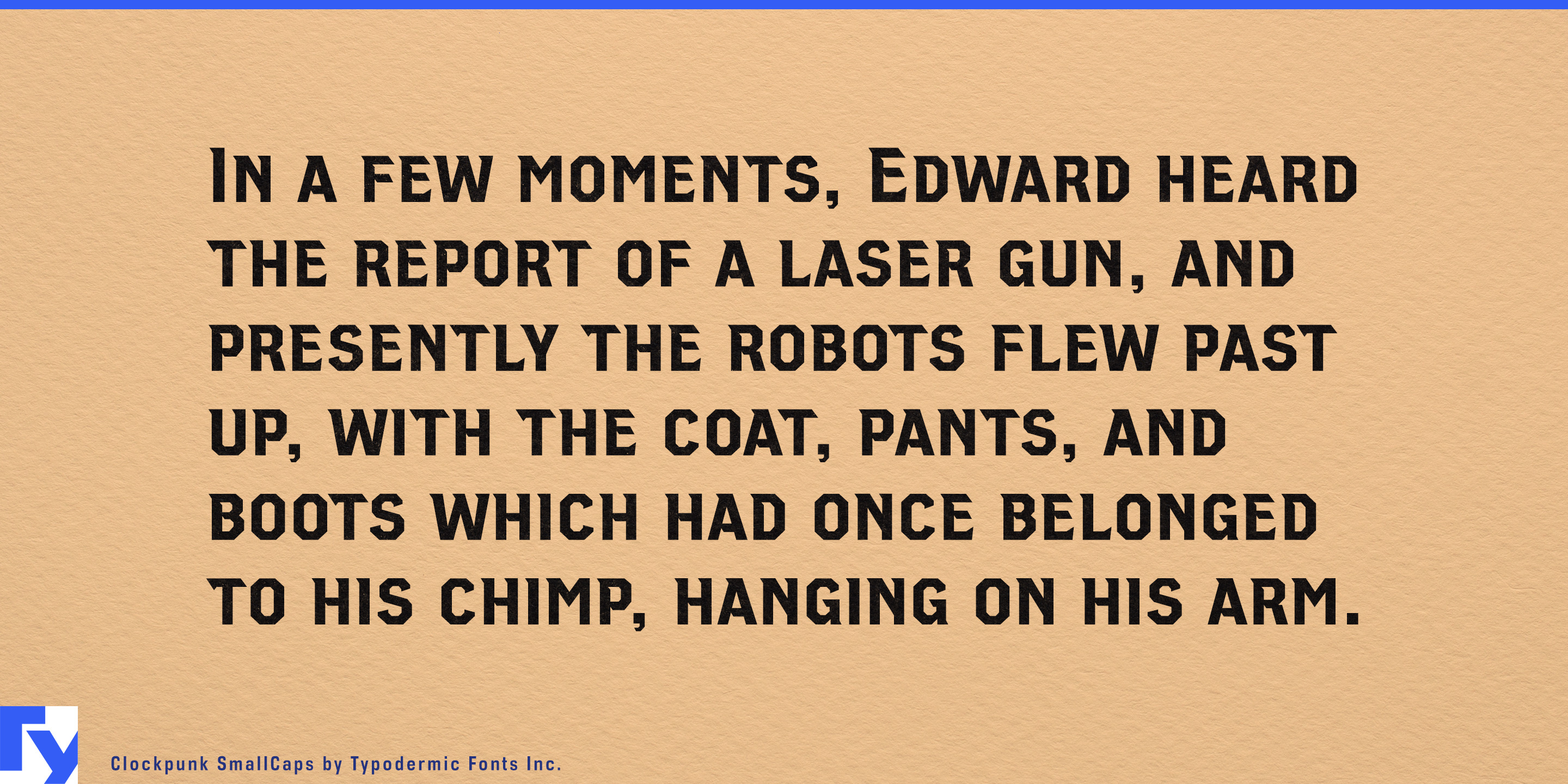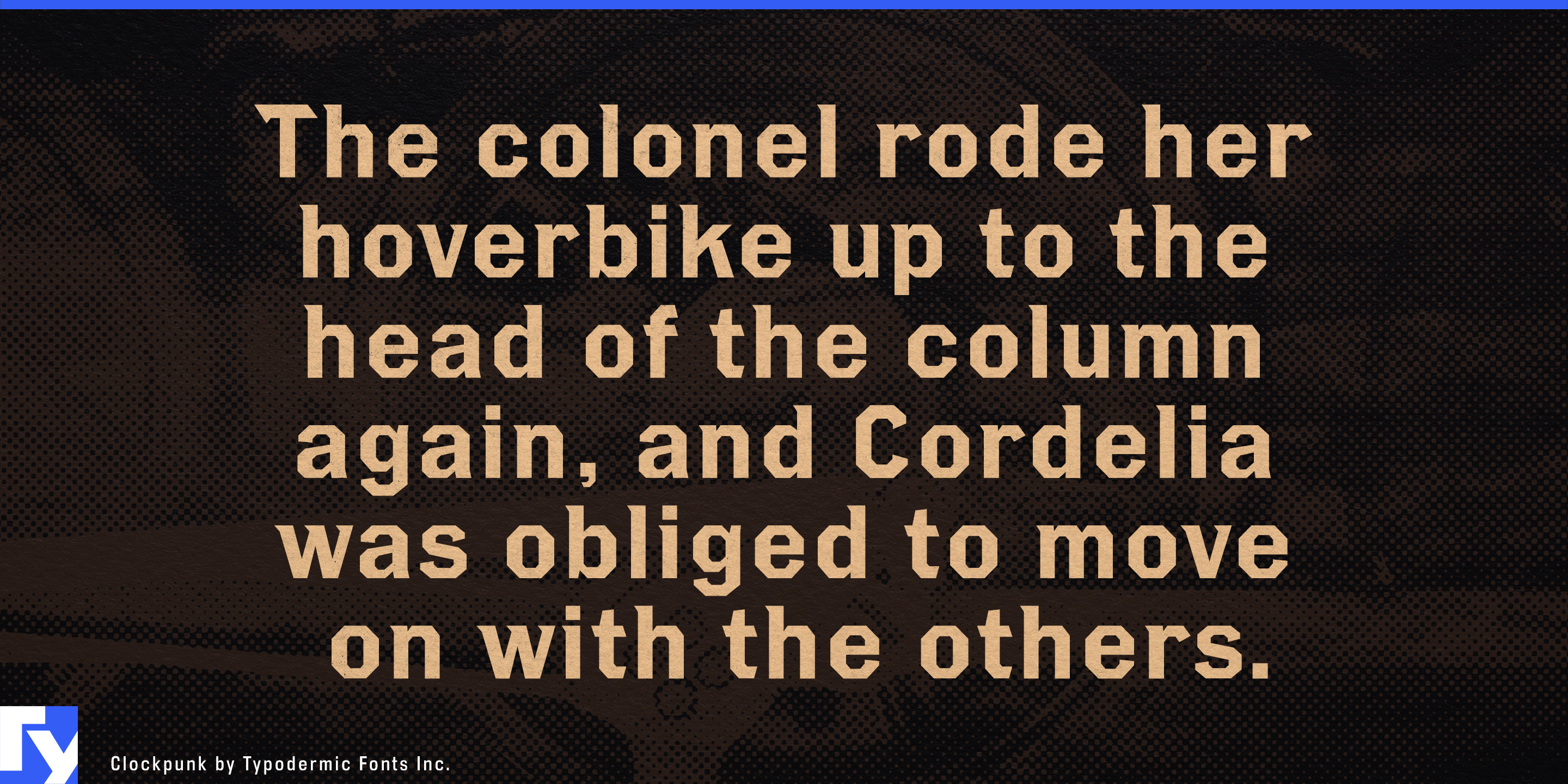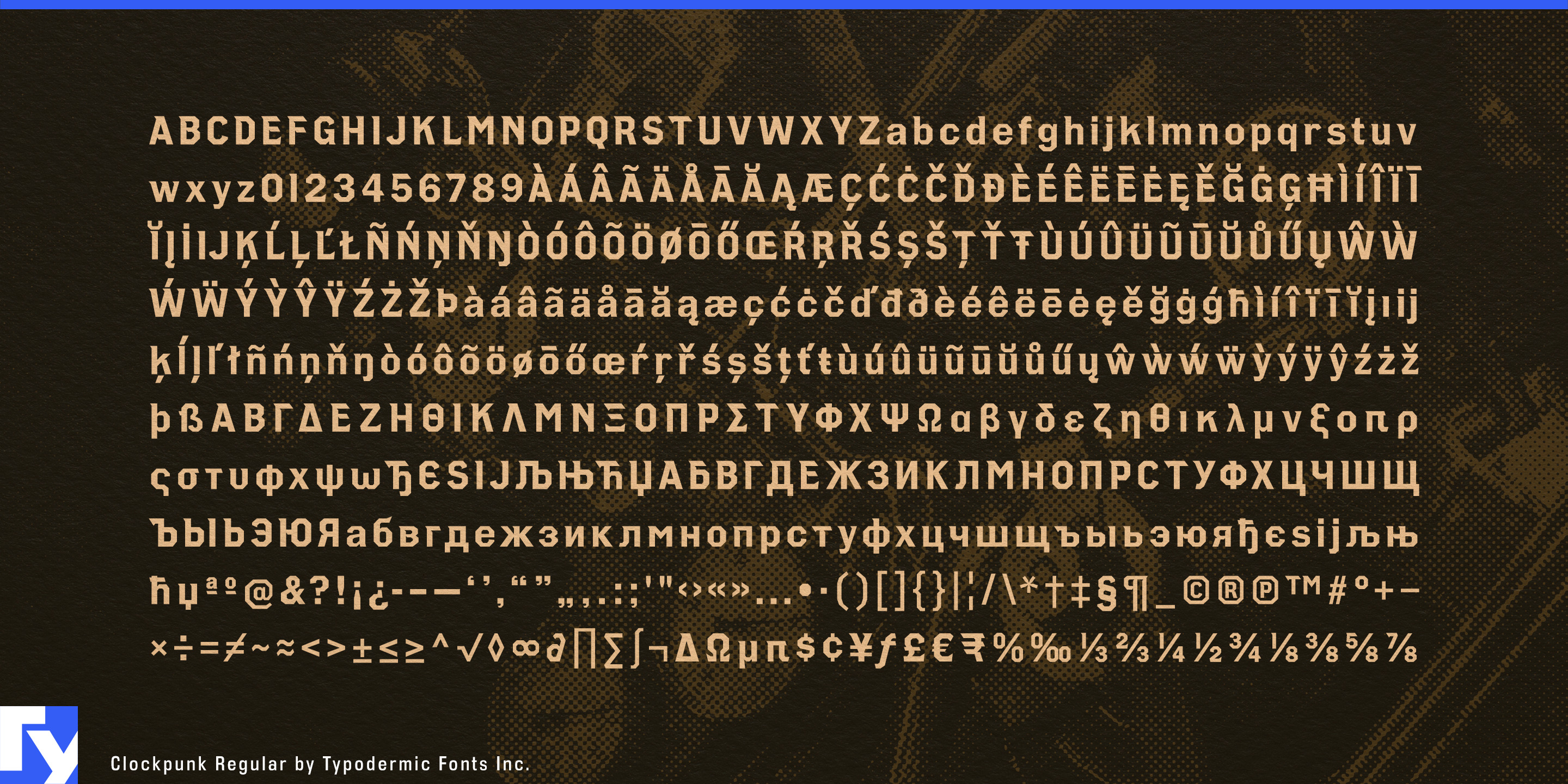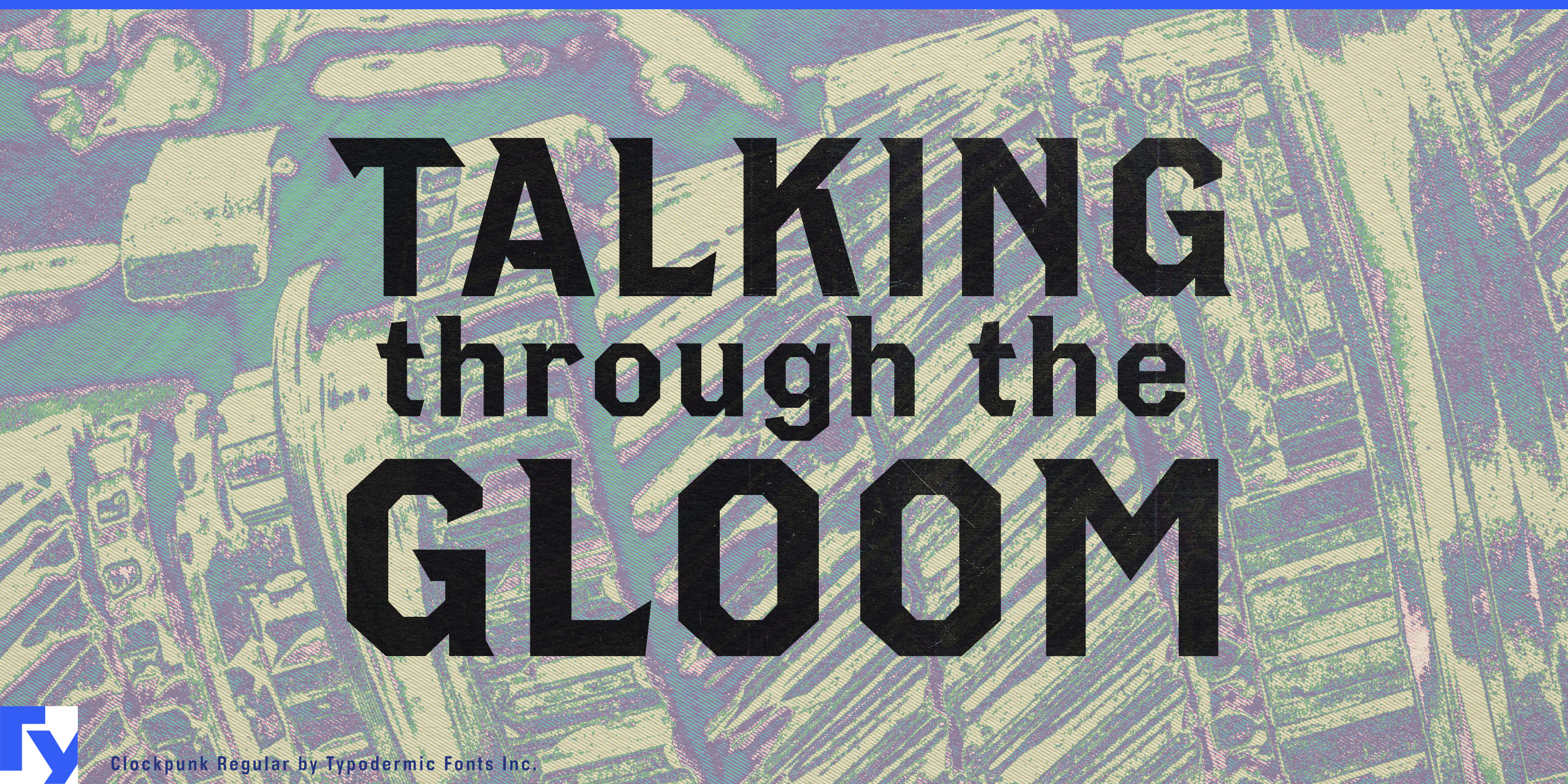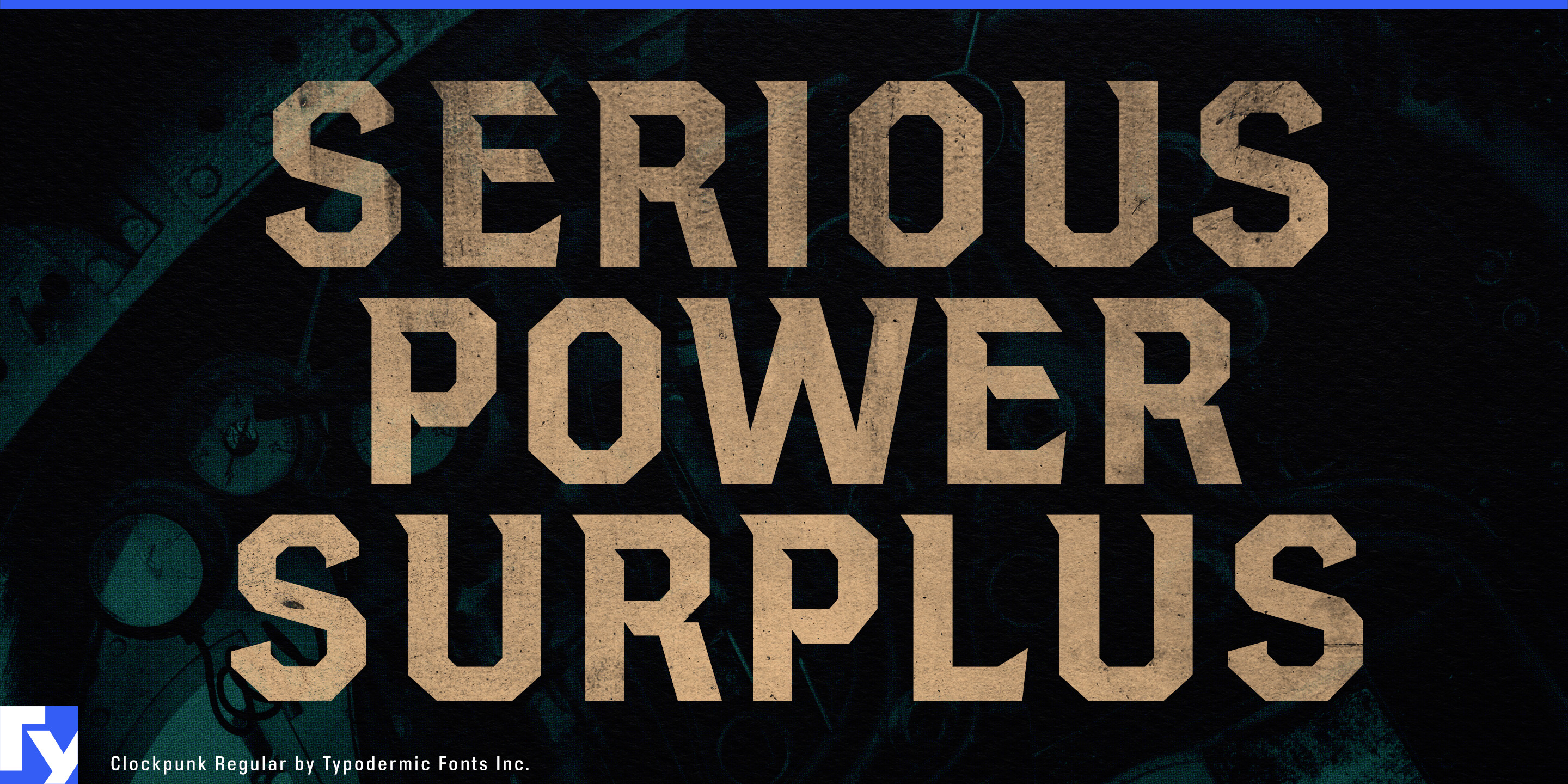
Clockpunk
Les identités rurales et industrielles se heurtent souvent au problème du déguisement typographique. Les polices western peuvent faire d’un produit sérieux un décor de saloon ; les lettres industrielles vieillies peuvent le pousser vers un univers tactique ou postapocalyptique ; une sans empattement neutre peut effacer tout sentiment de lieu. Clockpunk ouvre une autre voie. Son caractère anguleux issu du chemin de fer suggère machines, fret, dépôts, ateliers et infrastructures rurales en activité sans coiffer le projet d’un chapeau de cow-boy.
Clockpunk convient particulièrement aux équipements haut de gamme de cuisine en plein air. Fumoirs à foyer déporté, fumoirs à granulés, barbecues professionnels, planchas d’extérieur, cuisines extérieures modulaires et systèmes de cuisson au feu peuvent l’utiliser pour noms de modèles, écussons de séries, titres de panneaux de commande, visuels de remorques, présentations de distributeurs, emballages, équipements de concours et campagnes de lancement. Ses formes trouvent leur place près de l’acier, des cadrans, des roues, des poignées et de la chaleur, sans clichés de faux western.
Les équipements de pick-up et de remorquage se prêtent à cette même esthétique mécanique américaine. Boîtes à outils pour camions, rangements de benne, couvre-bennes, galeries, dispositifs de remorquage, éléments de suspension, éclairages, carrosseries utilitaires, accessoires de camping et matériel de voyage tout-terrain peuvent employer Clockpunk pour familles de modèles, plaques d’équipement, décalcomanies, catalogues, emballages, visuels de salons et présentations chez les distributeurs. Les équipements de propriétés rurales — petits tracteurs, tondeuses à rayon de braquage zéro, fendeuses de bûches, générateurs, pompes, véhicules utilitaires, rangements d’atelier et machines de transformation du bois — profitent du même caractère éprouvé et fonctionnel.
Les remorques relient naturellement ces univers. Remorques utilitaires, remorques-fumoirs, vans à chevaux, caravanes, cuisines mobiles, porte-engins et remorques de travail offrent de grandes surfaces pour un lettrage associé au transport et aux machines sans emprunter les codes des sports automobiles.
Les événements et lieux américains actuels peuvent employer Clockpunk sans basculer dans la nostalgie du Far West. Festivals country et de musique roots, rencontres mêlant barbecue et musique, séries de concerts en plein air, honky-tonks contemporains et établissements de bord de route peuvent l’utiliser pour titres d’événements, noms d’artistes, produits dérivés, visuels de scène et enseignes. L’atmosphère évoque davantage wagons couverts, relais routiers, dépôts et villes de travailleurs que badges de shérif et saloons.
Clockpunk fonctionne aussi dans les mondes fictifs construits autour des machines historiques. Jeux de rôle de fantasy historique, jeux d’histoire alternative, jeux de plateau, univers ferroviaires, attractions immersives, escape games et expositions d’histoire industrielle peuvent l’employer pour noms de factions, titres de quêtes, présentations de personnages, lieux sur les cartes, avis fictifs, menus, documents servant d’accessoires de décor, titres d’expositions et textes de décor.
Sa construction anguleuse repose sur des proportions prévues pour rester lisibles : l’atmosphère peut donc se poursuivre sous le grand titre quand un projet a besoin de noms, étiquettes, titres et informations changeantes. Clockpunk apporte l’histoire des machines et un caractère rural aux projets qui demandent quelque chose de plus robuste qu’une typographie neutre et de moins théâtral qu’une police de cow-boy.